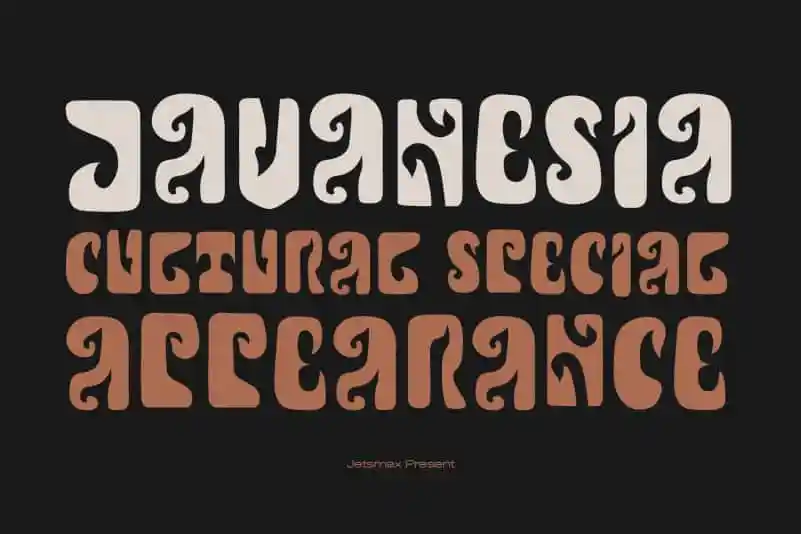
Javanesia Display Font – Download Grátis
Javanesia Display Font é uma fonte especial e única projetada para transmitir a riqueza e diversidade cultural das Ilhas Java, na Indonésia. Inspirada nos elementos artesanais e na arte tradicional do país asiático, essa fonte traz uma sensação autêntica de desenho à mão a qualquer projeto gráfico. Suas linhas curvadas e detalhes elaborados evocam o poder da cultura javanesa em sua forma original e singular. Perfeita para projetos que buscam um toque distintivo, Javanesia Display é uma escolha ideal tanto para design editorial quanto para identidades visuais, oferecendo uma maneira única de destacar seus trabalhos gráficos.